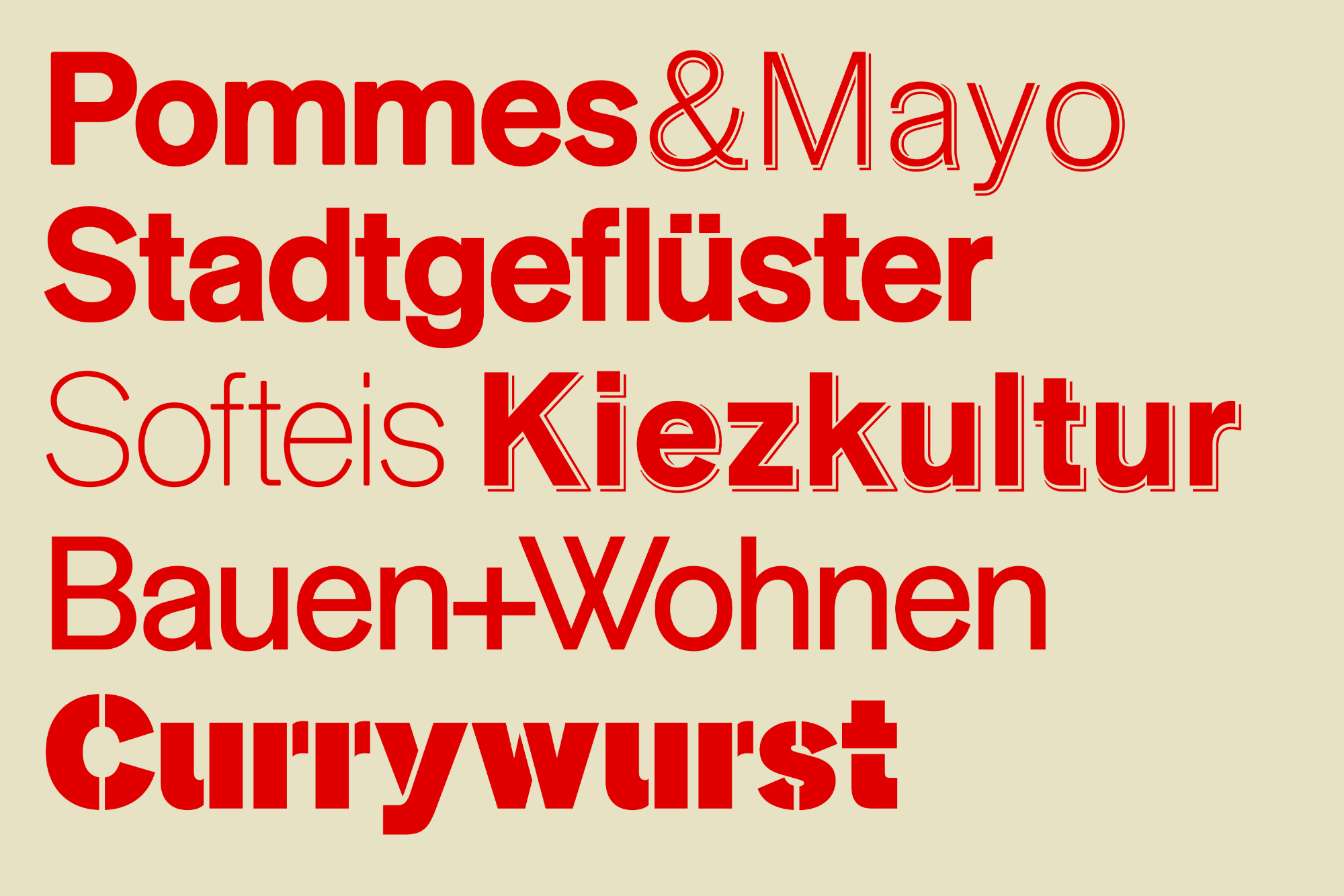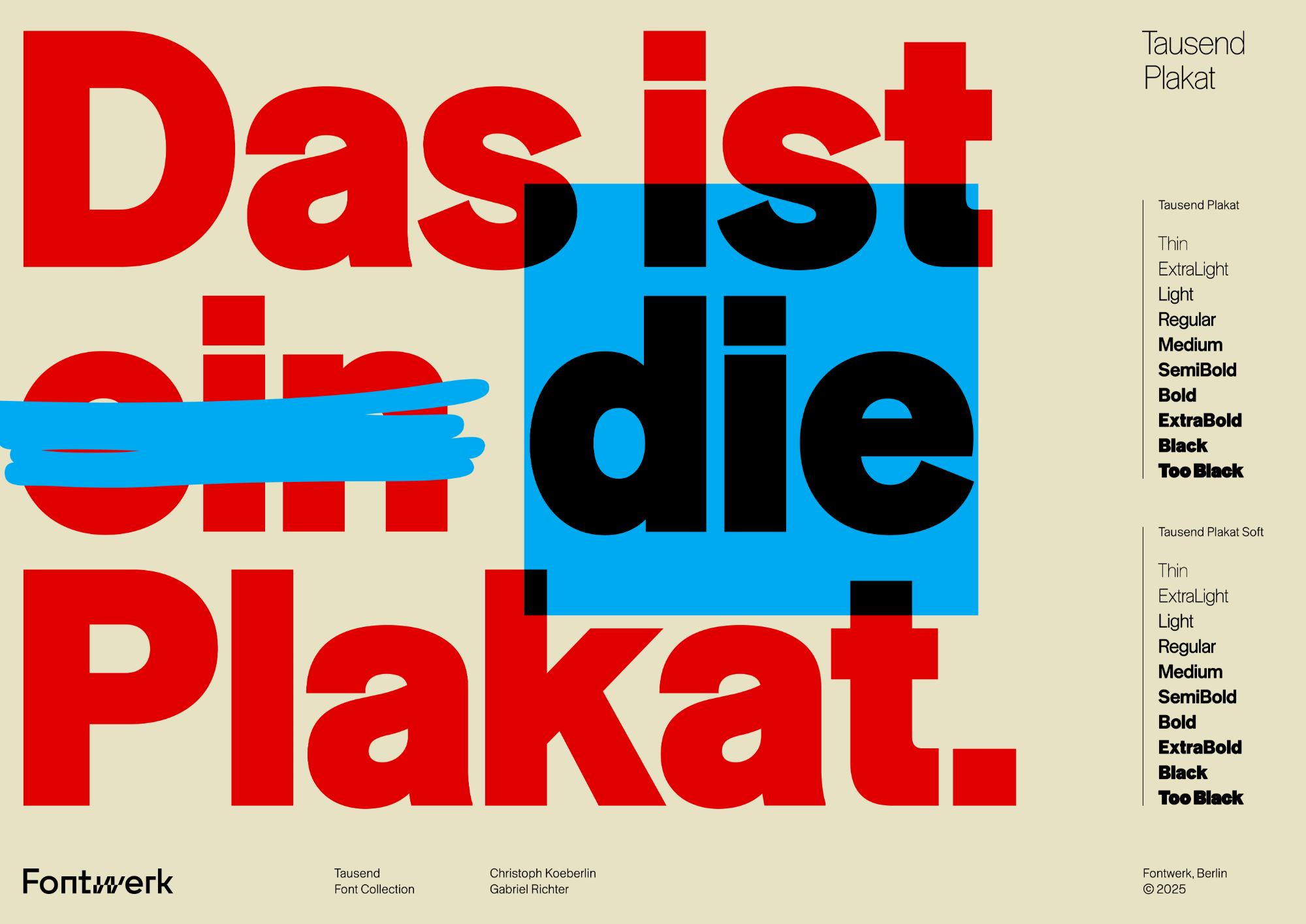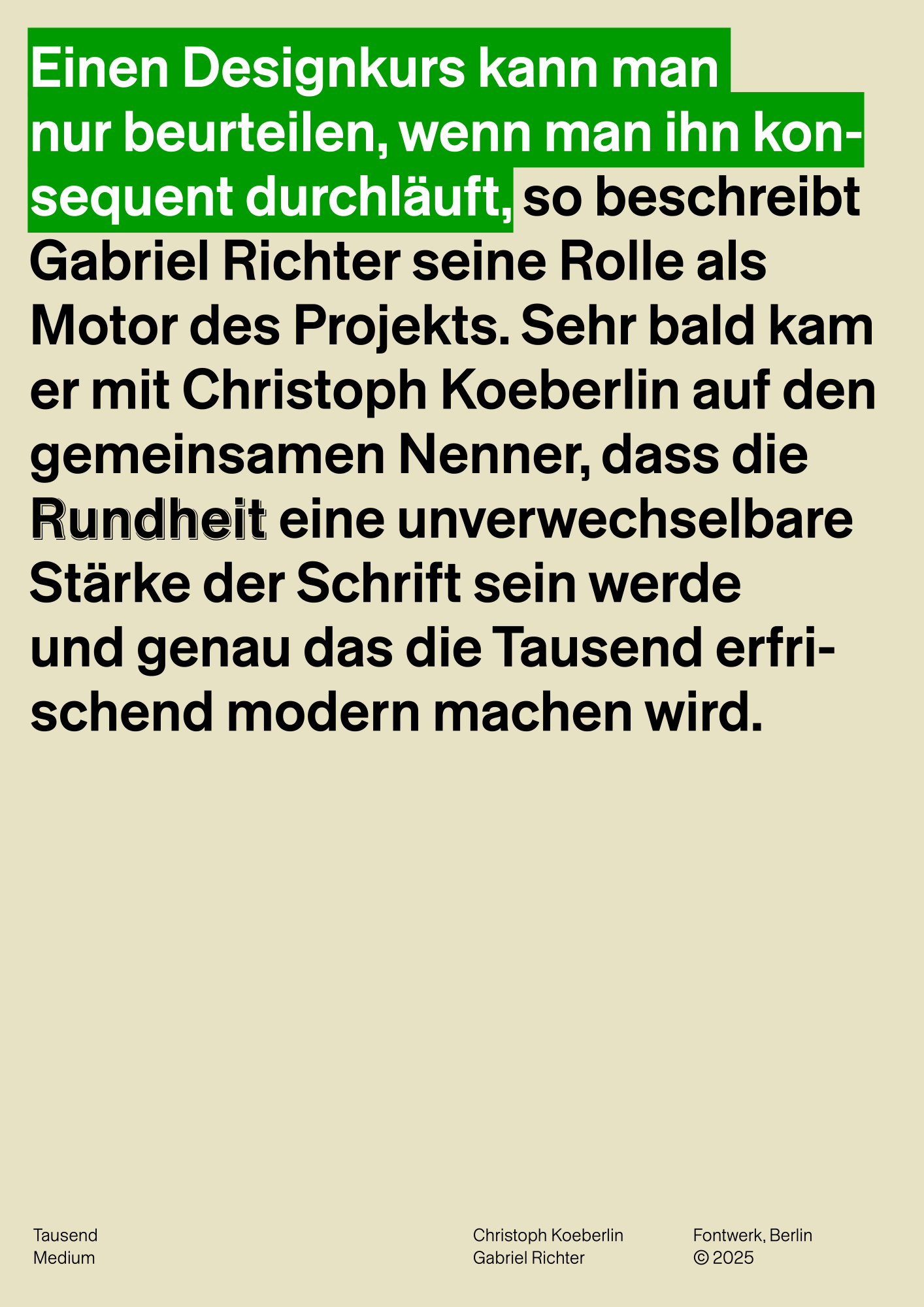
Die von Christoph Koeberlin und Gabriel Richter gestaltete statische Grotesk ist eine Schriftsippe bestehend aus sechs Familien: die beiden optischen Größen Tausend und Tausend Plakat (je zusätzlich als Soft-Variante) sowie die Tausend Stencil und Tausend Shaded.
Die Familie basiert auf der klassischen Idee neutraler deutscher Groteskschriften des 20. Jahrhunderts, wie etwa der robusten Akzidenz-Grotesk. Sie versucht jedoch, diese in Bezug auf Design, Erweiterung der Familie, Zeichensatz und Präsentation auf möglichst vielfältige Weise zeitgemäß neu zu interpretieren.
Die Basisvariante Tausend ist die ›neutralste‹ Variante der Sippe. Im Vergleich zur Tausend Plakat öffnen sich ihre Innenräume für kleine Schriftgrößen, während für große Größen die Tausend Plakat gestaltet wurde. Hier treten Details in den Vordergrund, am deutlichsten erkennbar am großen W. Ein geringerer Kontrast, kleinere Öffnungen, eine engere Zurichtung, mit Versalhöhe und Oberlänge abschließende Akzente und ungeschliffenere Formen ergeben eine dichtere und kompaktere Wirkung im Vergleich zur Basisvariante.
Parallel zur ›klassischen‹ Tausend mit der optischen Größe Plakat gibt es die in gleicher Weise ausgebaute Tausend Soft, eine statische Grotesk-Großfamilie mit dezent abgerundeten Ecken. Alle vier Unterfamilien enthalten neun Strichstärken von Thin bis Black, mit TooBlack steht es zudem ein zehnter Fettgrad zur Verfügung, der über die fettesten Strichstärken anderer Schriften hinausgeht.
Zwei weitere Versionen der Tausend zielen auf den Einsatz in Schaugrößen. Die Schablonenversion ist eine Reminiszenz an die digital nicht mehr erhältliche AG Book Stencil, 1985 entworfen von Günter Gerhard Lange. Auch Tausend Stencil wurde als variabler Font entwickelt, inklusive einer Achse, über die die Lücken bzw. Stege verbreitert oder verschmälert werden können.
Die sechste Unterfamilie Tausend Shaded weist einen Schattenwurf auf, der sich optisch korrekt an das Gewicht anpasst und als weitere Hommage an die AG verstanden werden kann, nämlich an ihr erstes Auftauchen unter dem Namen ›Schattierte Grotesk‹ im Jahr 1895.
Dank des Latin-M-Zeichensatzes werden 400 Sprachen unterstützt, darunter europäische und afrikanische sowie Vietnamesisch, aber auch der gesamte DIN-91379-Standard.
Die komplette Tausend-Collection enthält sechs Einzelfamilien: Tausend, Tausend Plakat, Tausend Soft, Tausend Plakat Soft, Tausend Stencil und Tausend Shaded
Schriftmuster Tausend Collection